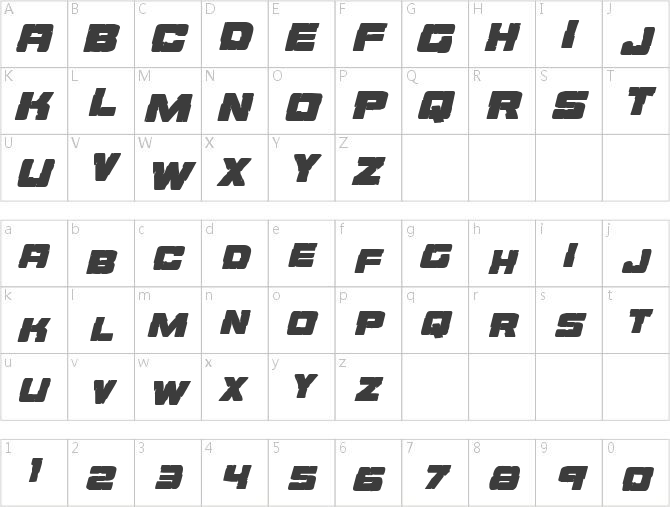
Ore-Crusher-Bold-Italic
Ore-Crusher-Bold-Italic介紹
Ore-Crusher-Bold-Italic字體字庫是一款讓人賞心悅目、百看不厭的英文字體,適合各類廣告和產品包裝設計應用,字體大小0.08MB,格式為ttf字體,上傳用戶是yinjun,作者/版權方為未知